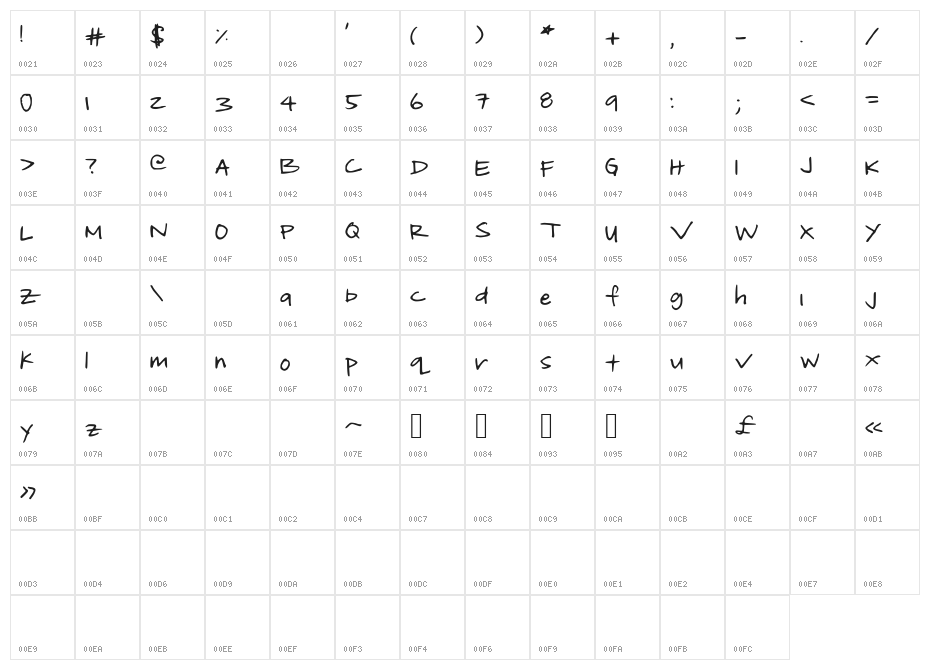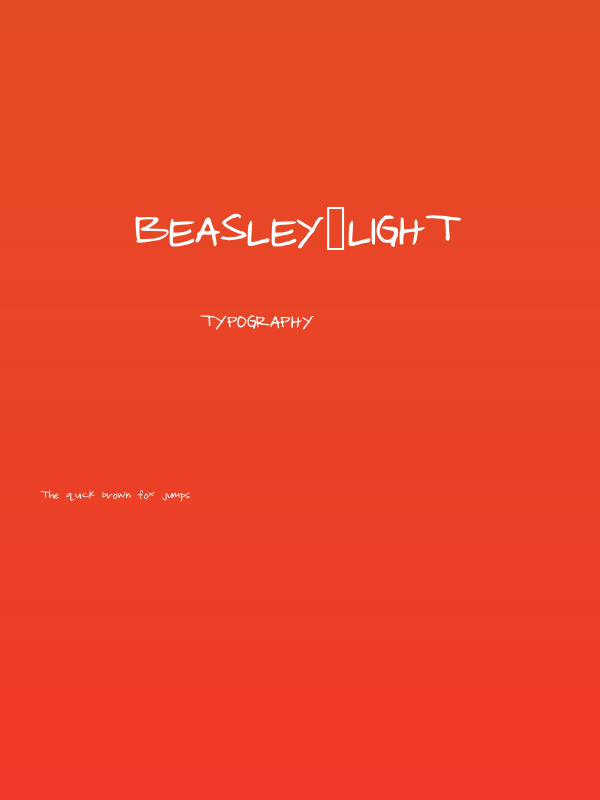
Beasley_Light Font
| Stile generale | Casual |
| Caso d'uso | Logos, Headlines, Informal Text |
| Progetti proposti | Ideal for greeting cards, personal notes, informal invitations, and creative projects that benefit from a personal touch. |